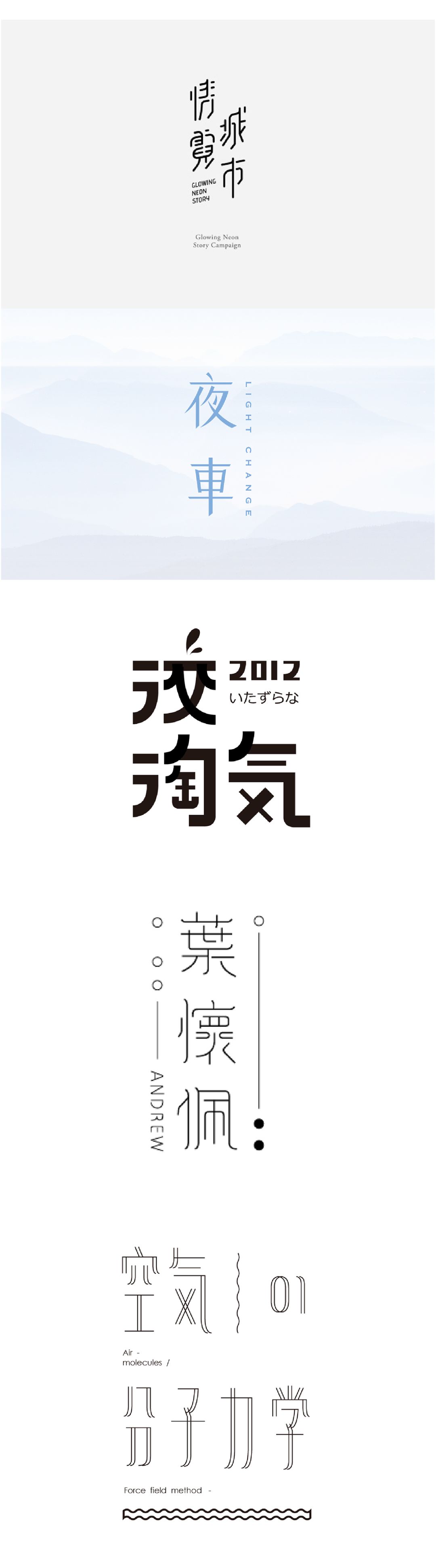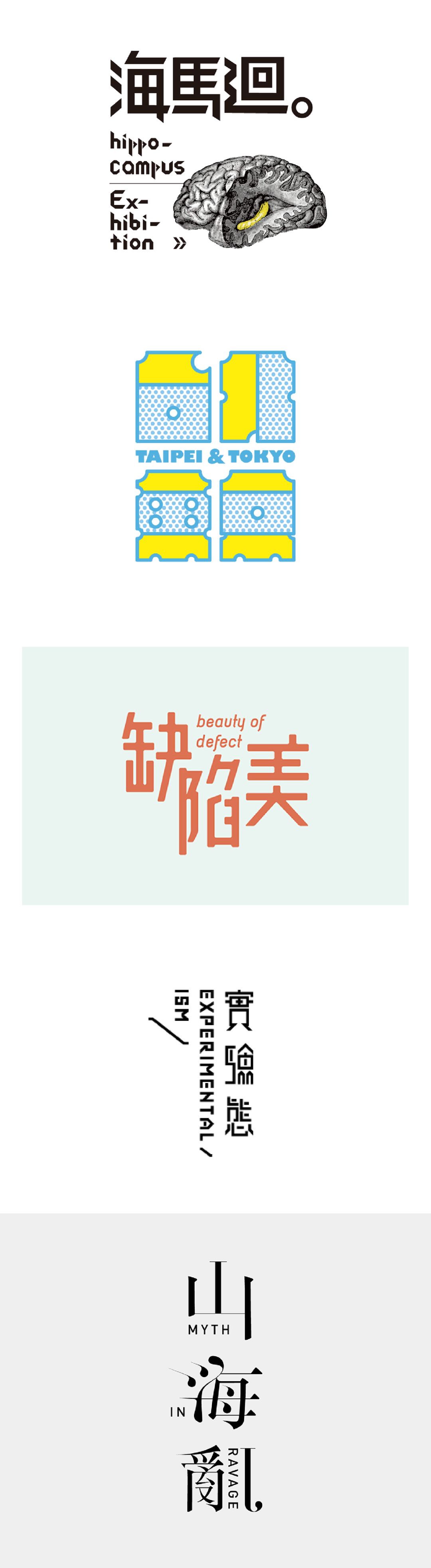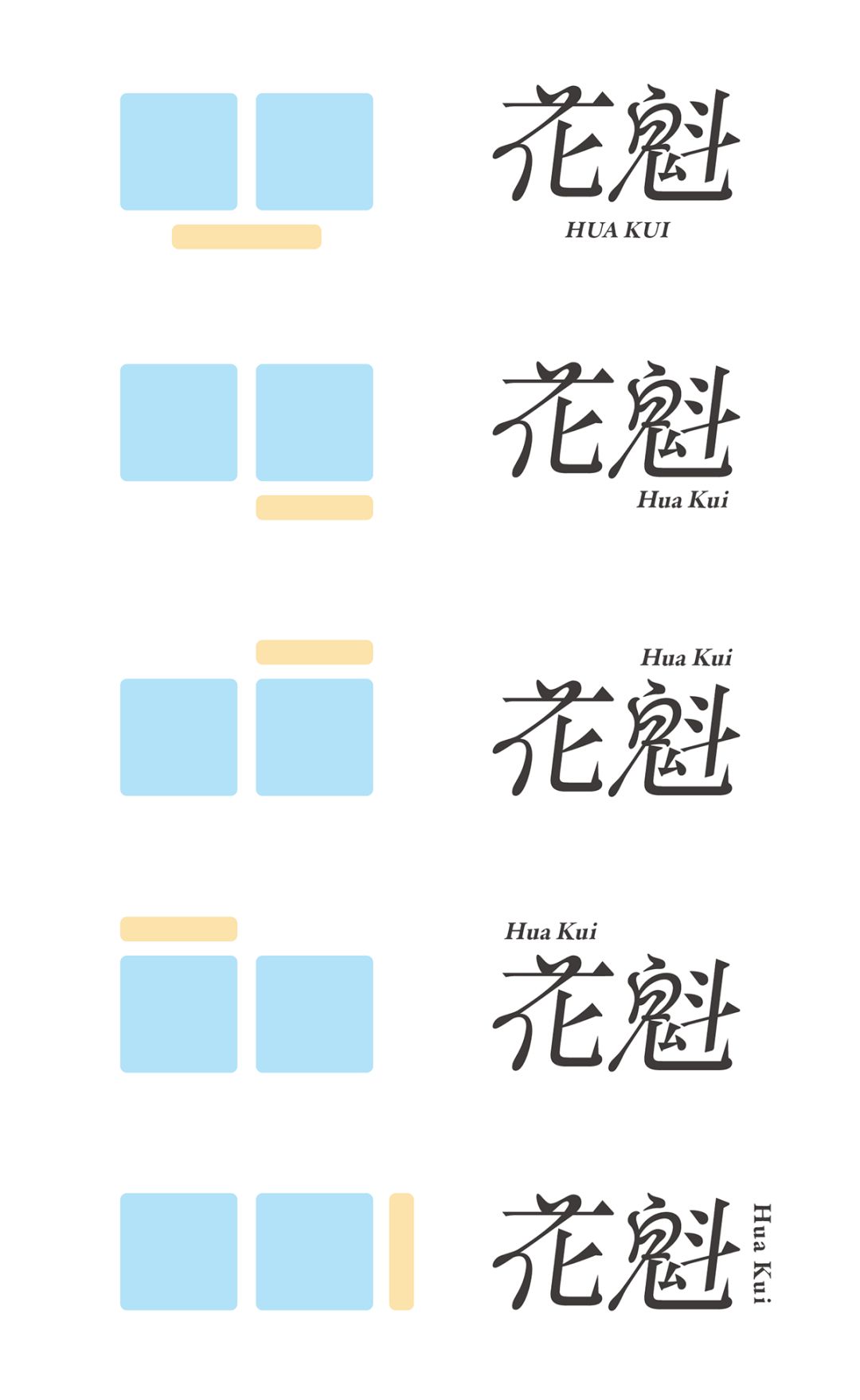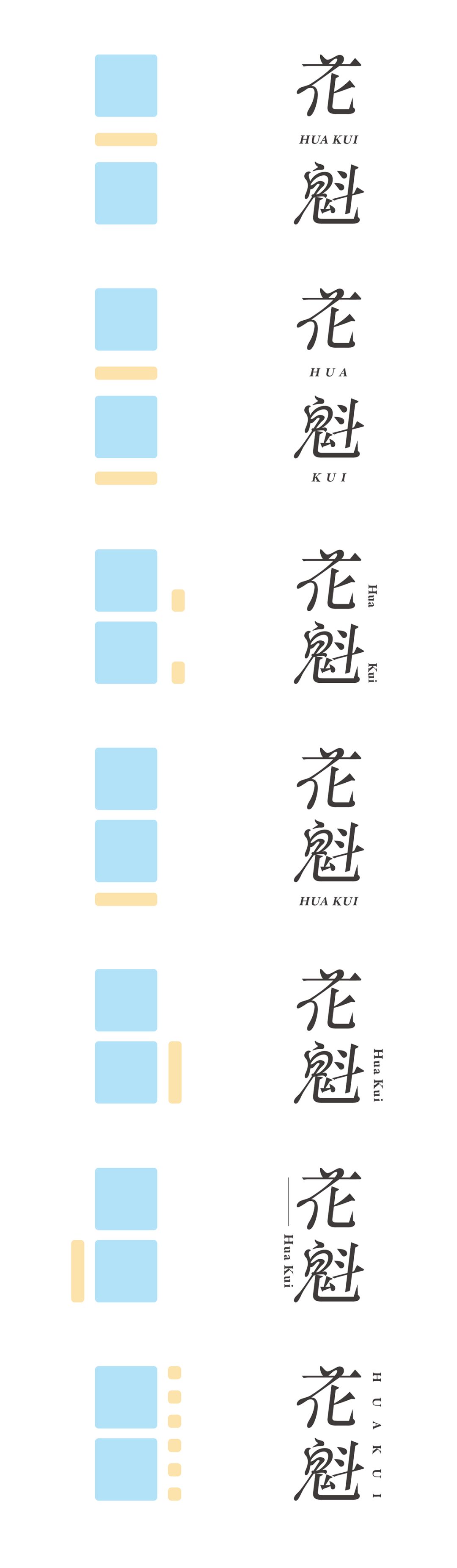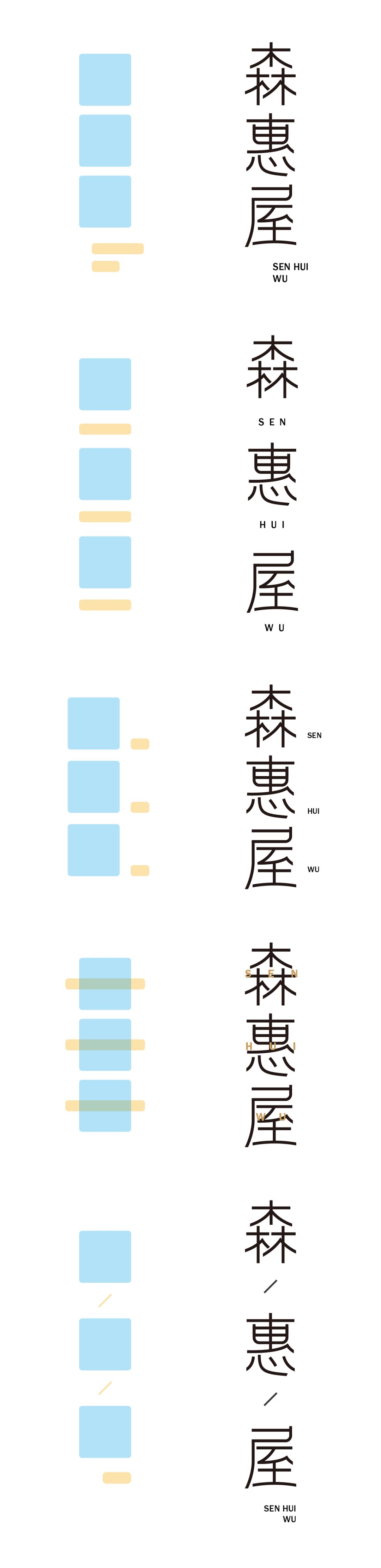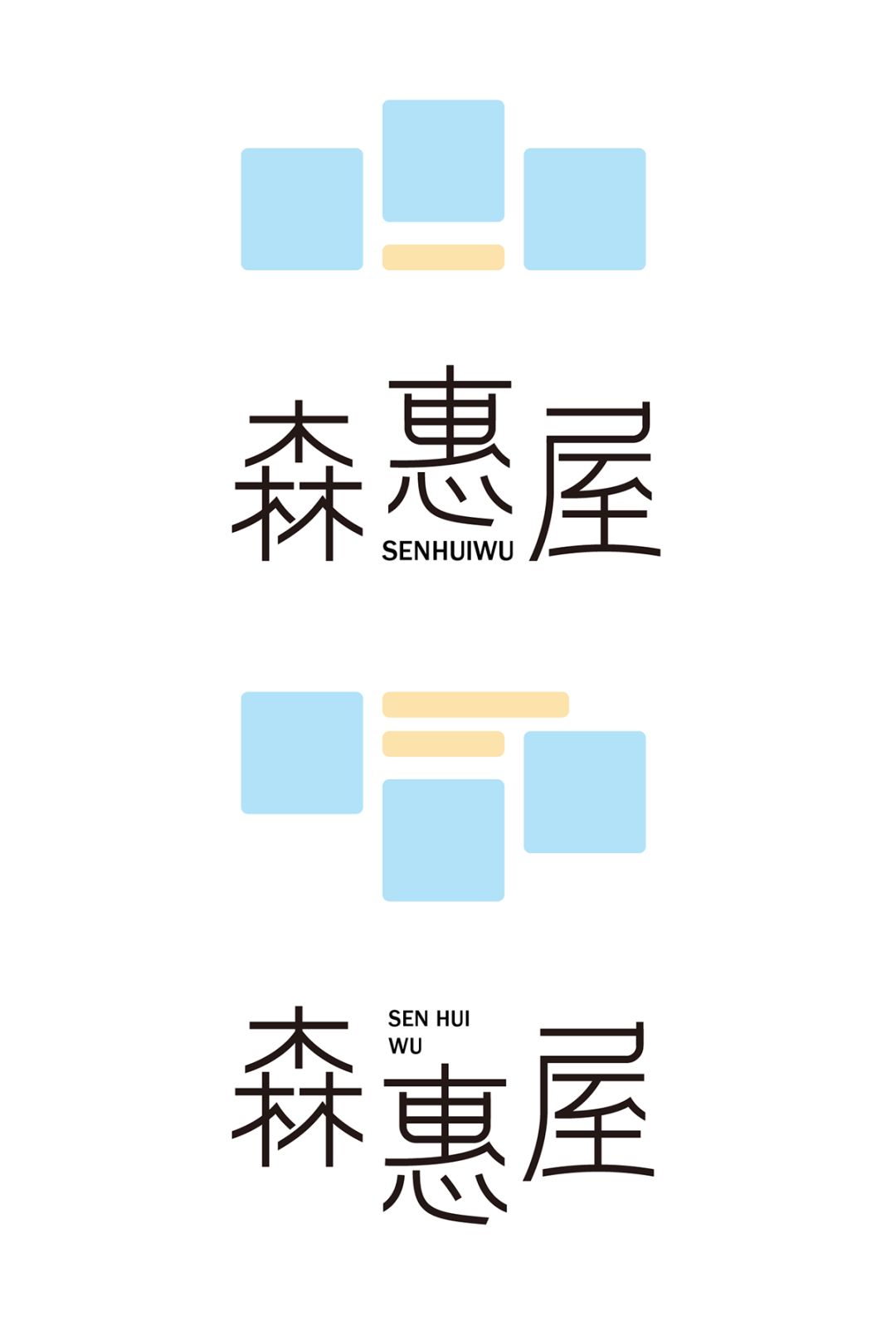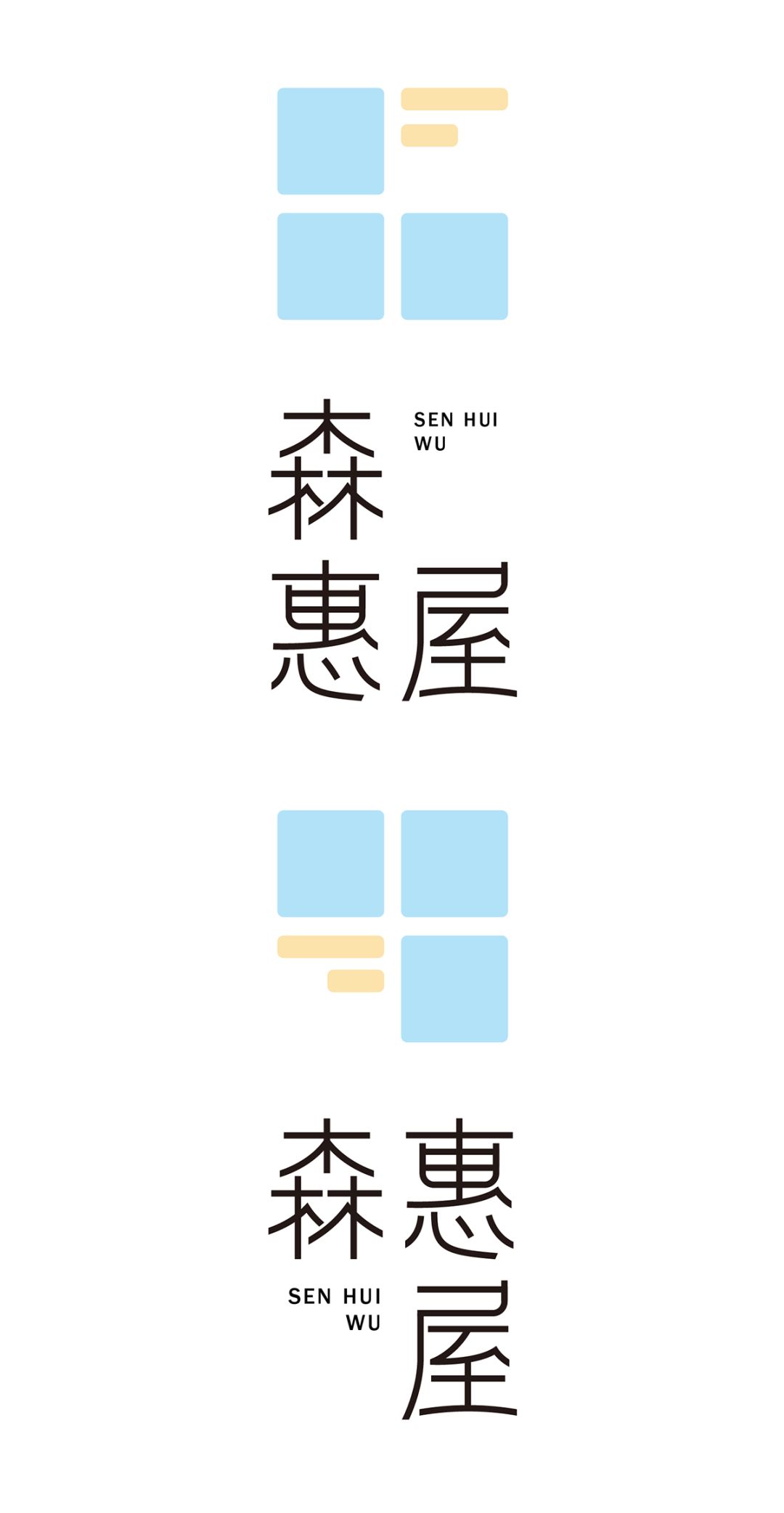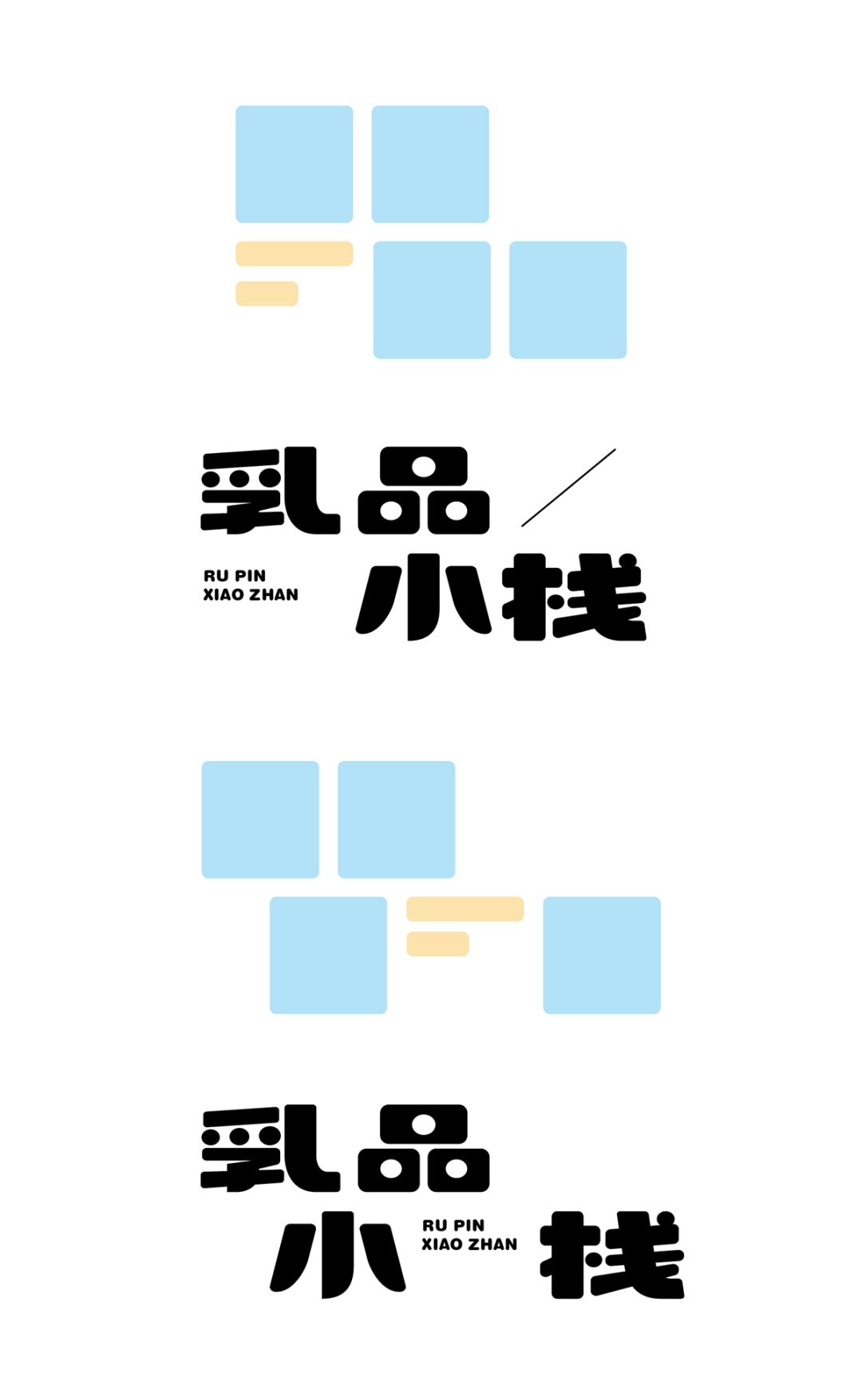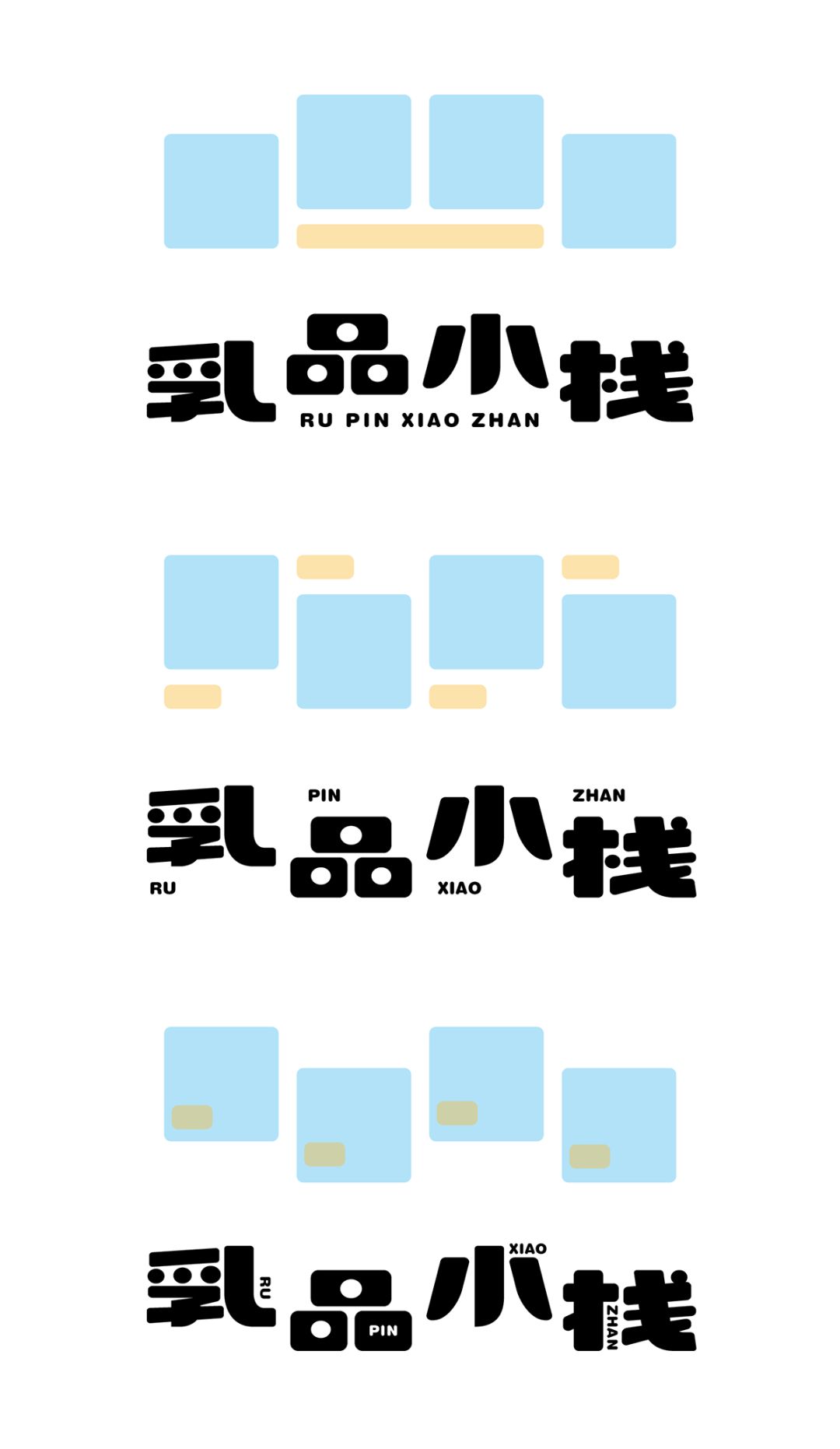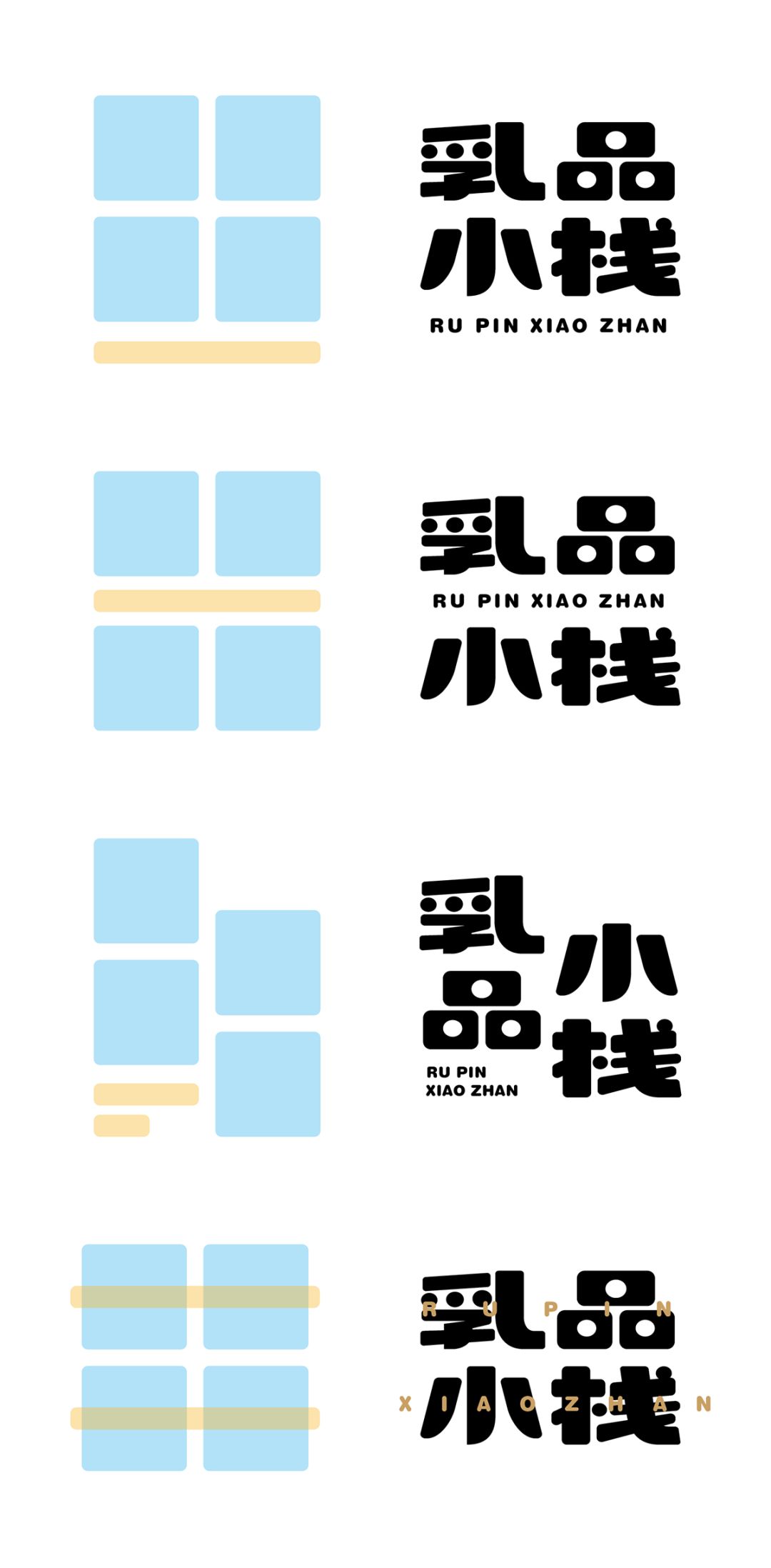
不同的编排方式会给字体带来不同的面貌,咱们先来看一下优秀的字体设计作品,直观的看到他们通过不同的编排方式,给字体设计作品所营造出不同的氛围。当然,字形设计的优劣也尤为重要,本文主要探讨的重点是中英文编排方式而非字体设计本身。
下图的设计作品基本都是出自日本、台湾、香港,因为他们的编排方式比较新颖,同时又不失简约之感~
好东西看过之后,咱们开始正式步入正题!整理了一些常见的编排方式,以图析和案例的形式直观的展现出来,并且通过字数进行了简单的分组,那么咱们走起!
首先是最为常见的横排方式,比较的端正。
同样是横排,通过英文的穿插来增强作品的形式感。
稍微灵活一些的错位编排,使用英文来填补留白。
接下来是竖排的方式,其实就是将横排的方式竖置。
三个字的编排相比两个字更加的灵活些,可以做一些大小的对比来起到强调的作用!(友情提示:上面展示过的一些常见的编排方式下面将不再进来罗列了。)
错位编排的方式都是很相近的,都是使用英文来填补留白。
还有一种错位编排的方式,就是字与字之间通过笔划的互补关系使得他们更加的整体,这种灵活的方式在卡通类型的字形中非常常见。
下面还单独列举了出来。(由于本次重点在于编排方式,故案例仅使用统一字形示意)
类田字形的编排,通过下图可以观察到一种现象,小号的英文是可以增强形式感的,原因是由于缩小后的英文会以点或面的形式存在了,这样偏构成形式的元素是增加形式感的途径。
下面是竖排的编排方式。
使用英文与字形融合,注意融合的要和谐,不要过于牵强。
四字的编排方式就更加多样了,从最常见的横排方式开始。
错位的编排方式使得字体更加的活跃生动些。
田字形编排使得字体显得更加的整体些。
在田字形的编排加以错位的形式,都是首字靠前,这样符合人们的阅读习惯。
在田字形的编排加以错位的形式,线条的加入是可以增加形式感的方式。
综上向大家展示了从二字到四字的常用编排方式,可以明显的看出不同的形式给字形带来了不同的面貌与性格,当大家接到某种属性或特征的字体设计需求时,不仅字体设计的本身很重要,编排的方式也尤为重要。